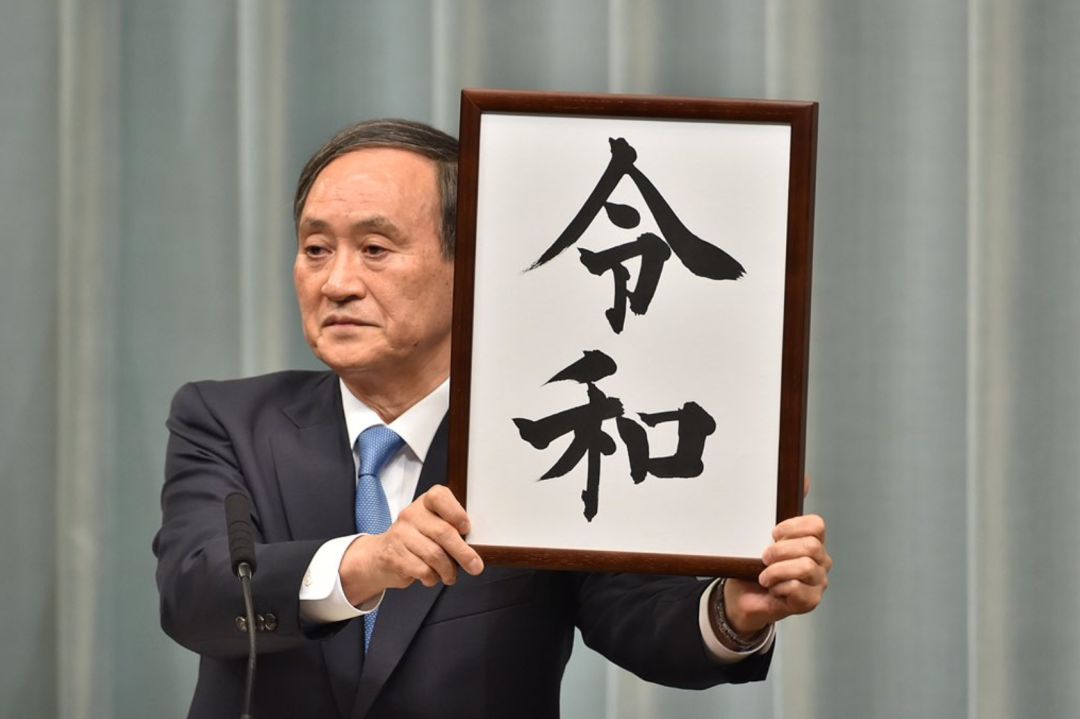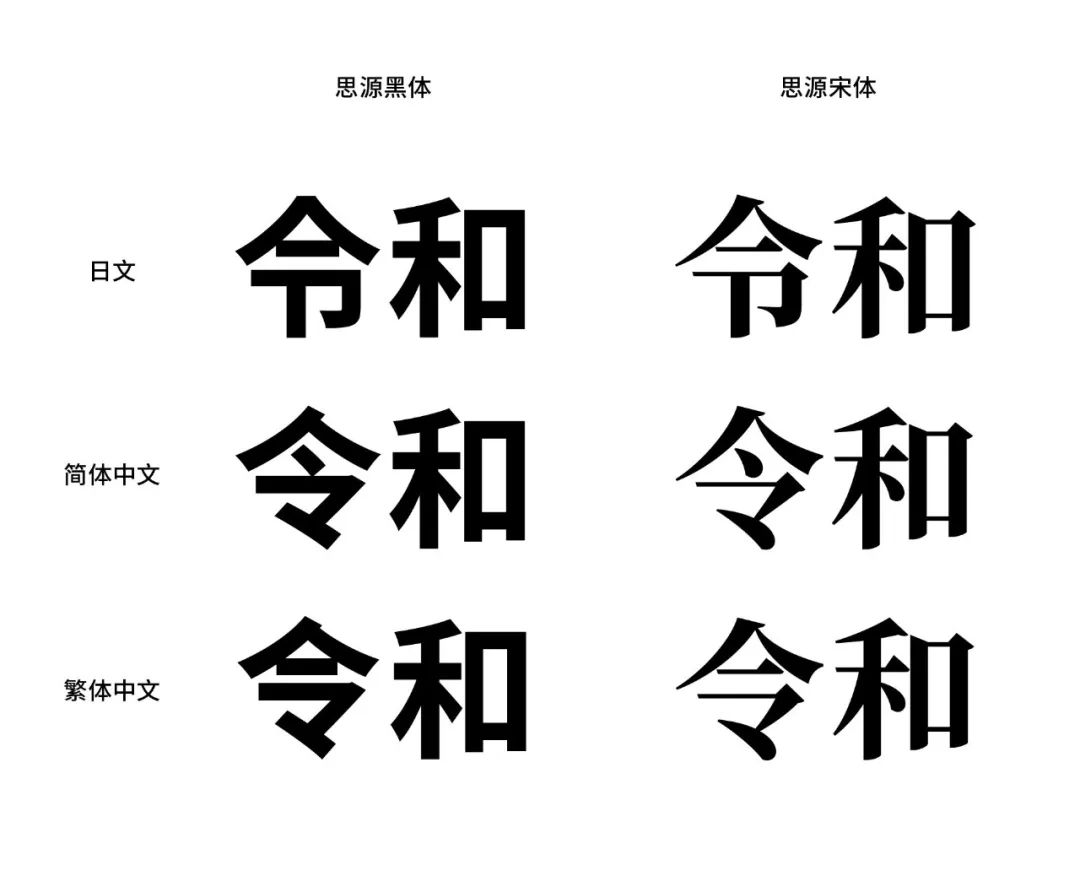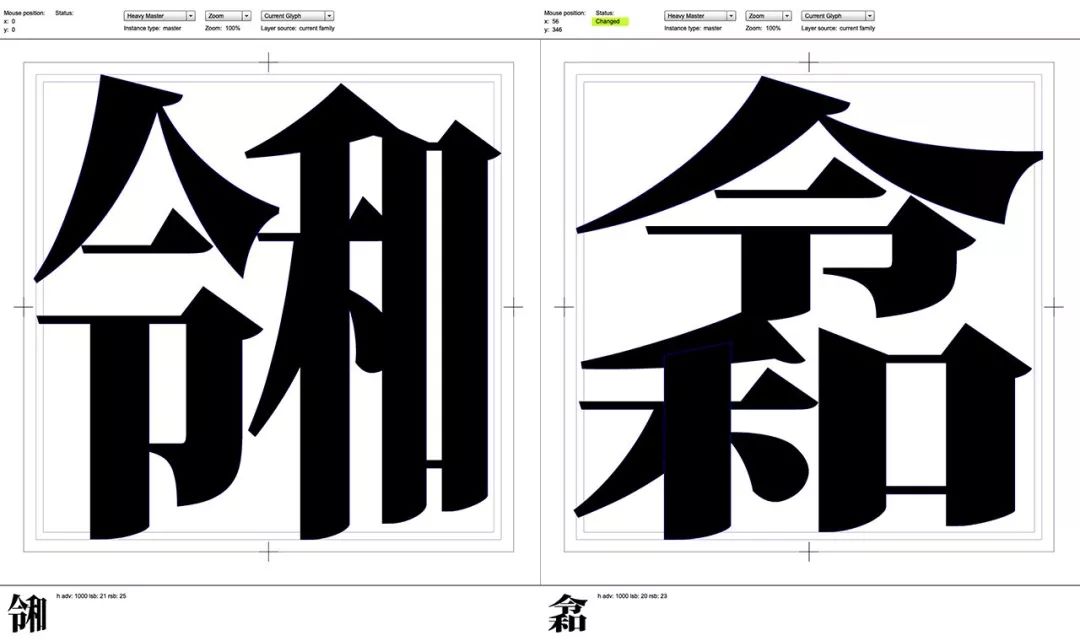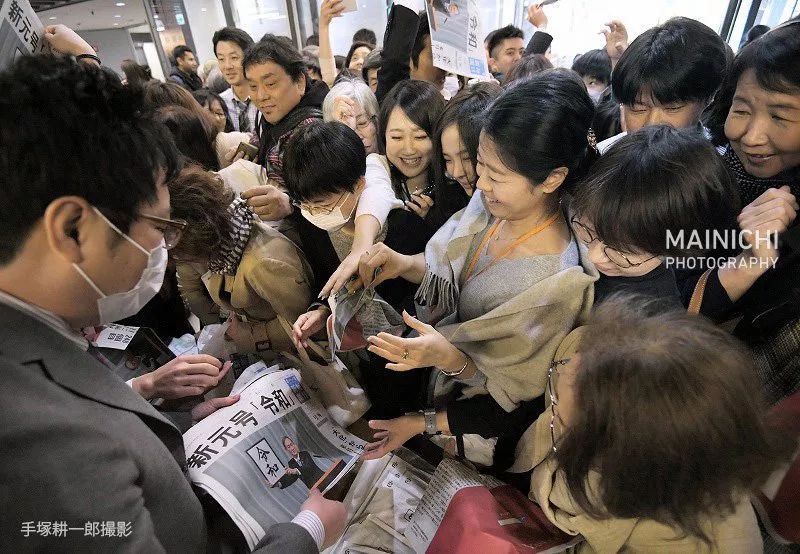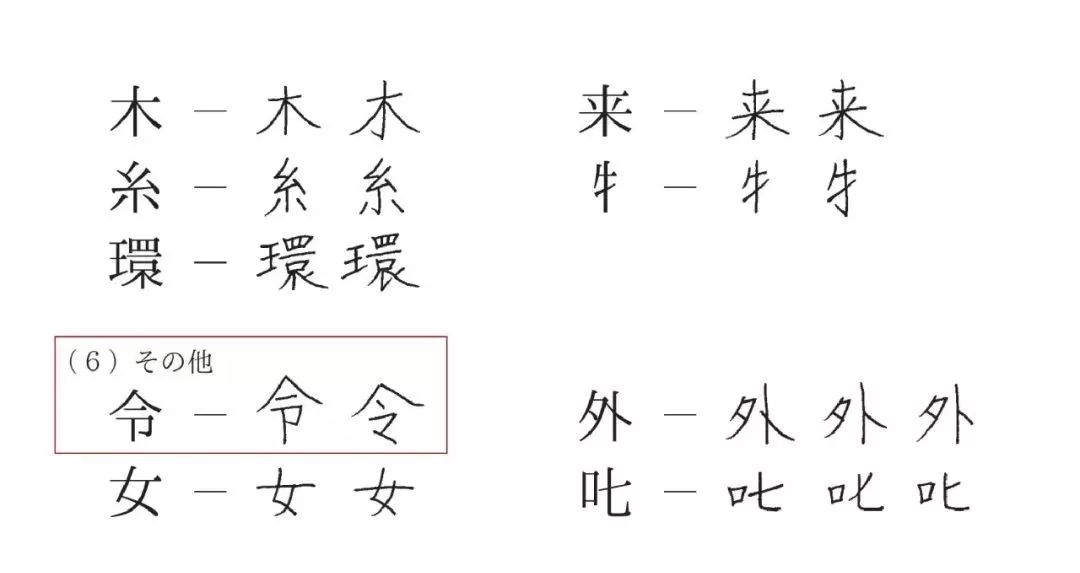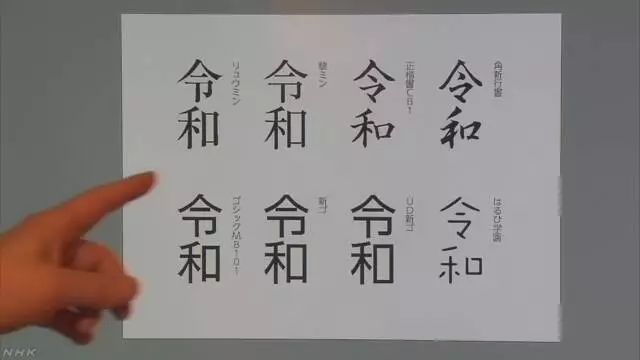
关于日本新年号「令和」,你可能不知道的五个事实
最近,日本政府严肃地在首相府邸召开新闻发布会,正式宣布下一轮年号名称为「令和」。在字体设计师眼中,改年号不仅是国家层面上的大事,对实际业务也有直接的影响。小编在 twitter 上关注了不少字体设计师,整理了一些关于「令和」的有趣事实,让我们和日本人民一起来凑个热闹吧:
❶
年号的「合字」
年号对于日本人来说是非常重要的汉字组合,所以字体厂商们往往会把它们做成 「合字」,将两个文字压缩在一个全角文字的空间内,既彰显了年号的威严,又会显得更整齐美观。比如之前的年号,是这样显示的:
㍾ ㍽ ㍼ ㍻
昨天年号刚发布之后,Adobe Font 就抓紧赶工制作年号合字,随即发文说明他们的小塚明朝体、小塚黑体(小塚ゴシック)和思源黑体(源ノ角ゴシック)日语及泛中日韩的版本,「令和」的合字已经更新完成。
Adobe Fonts 发布的小塚明朝体合字预览
由于日本保留了竖排阅读的习惯,所以在制作合字的时候必须同时制作横排和竖排的合字。制作的时候不仅仅是把两个字压扁然后放在一个框里,在一个全角字框里塞满两个字的同时要保证可读性和优美程度,字体设计师得使尽浑身解数才能做到完美。
❷
中日文的「令」不一样
大家都知道日文使用汉字,但实际上日汉字和中文汉字时常有一些细微的区别。比如“天”字,在日汉字里是上面的横比下面长,小编刚学日语的时候按照中文来写,就被老师打了个大大的 ❌。在「令和」中,「令」字也是个不老实的家伙,它在日文、简体中文和繁体中文的汉字造型都不大相同。如上图,以开源字体思源字体家族为例,「令」字的造型各不相同,正在学习日语和繁体字的朋友们可要多加注意了。
❸
日文的「令」也有好几种写法
不仅日文和中文的「令」有细微的差别,其实日文的「令」也有好几种写法。如上图所示,主要有两个地方的不同:人字头下面的点是横还是点;下半部分的整体造型是「卩」还是「マ」。不同的字体厂商也会根据字体的种类和风格选择采用哪种方案,似乎并没有一个定论。
日本有一个叫做《常用汉字表》的汉字规范,里面归纳了一般的新闻报刊以及日常生活中所用到的2136个字以及书写规范。其中在手写体的「令」中就有两种写法:
《常用汉字表》
进一步地,在《关于常用汉字表的字体字形的指示》(『常用漢字表の字体字形に関する指針』)文档中,对「令」的不同写法又有了更多的归纳:
《关于常用汉字表的字体字形的指示》
针对这个问题,日本文化厅的回复是「没有正确的答案」。在指示文档中,文化厅的观点是,汉字造型无法完全统一是书写习惯造成的,本来就不是一个问题,因此也不需要确定一个说法。
❹
「令和十八年」= R18 ?
🔞
日本改年号有几个规则,其中一个便是首字母不能与之前的年号重复,因为简写的时候常写成「首字母+年数」的形式。比如今年是平成三十年,也会记作H30。本次的「令和」罗马音是「reiwa」,首字母是「R」,也是小编最喜欢的一个西文字母。不过,这个小「R」也引发了推特网友的热烈讨论:因为R在电影分级制度中也会被使用,那么到了令和十八年就会简写成「R18」,即「十八禁」之意,2036年代表了🔞?关于改年号的讨论在推特上持续火热,日本网友真可谓是脑洞大开。
❺
改年号还要发「号外」
看过抗日神剧的朋友们大概都知道「号外」是什么,当有突发重要新闻时,报社便立即赶制版面,一个多小时后于当地街头派发,以求将消息尽快提供给读者。现代社会连报纸都几乎无人问津,但日本仍然保留了发「号外」的习惯。年号发表当天下午1点左右,各大报社纷纷开始在各大车站发放「改元」号外,抢夺的人群络绎不绝。
有趣的是,报社除了发布实体的号外,还在官网上发布pdf版本的「电子」号外。上一次改年号还是在三十年前,数字排版尚处萌芽时期,pdf版本的号外是不可想象的。让我们来看看各大报社的「号外」分别长什么样:
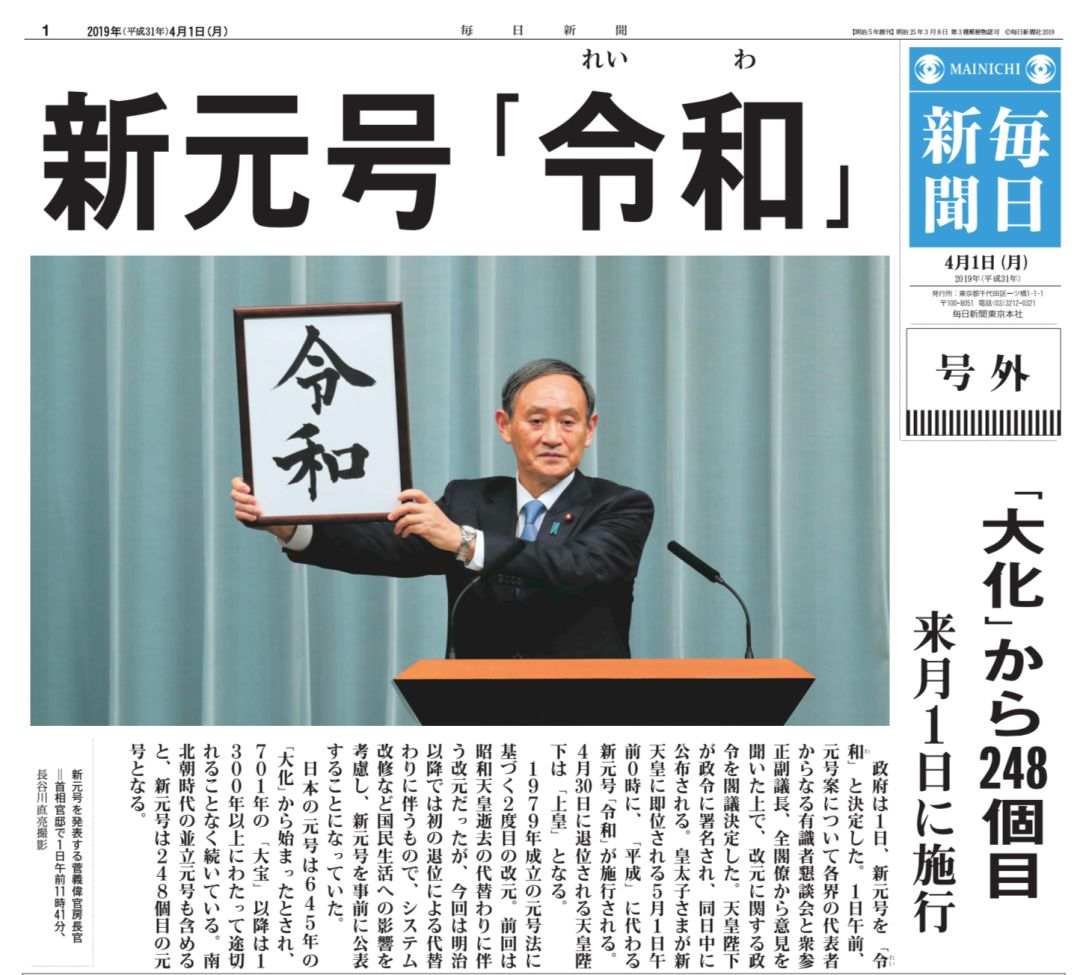
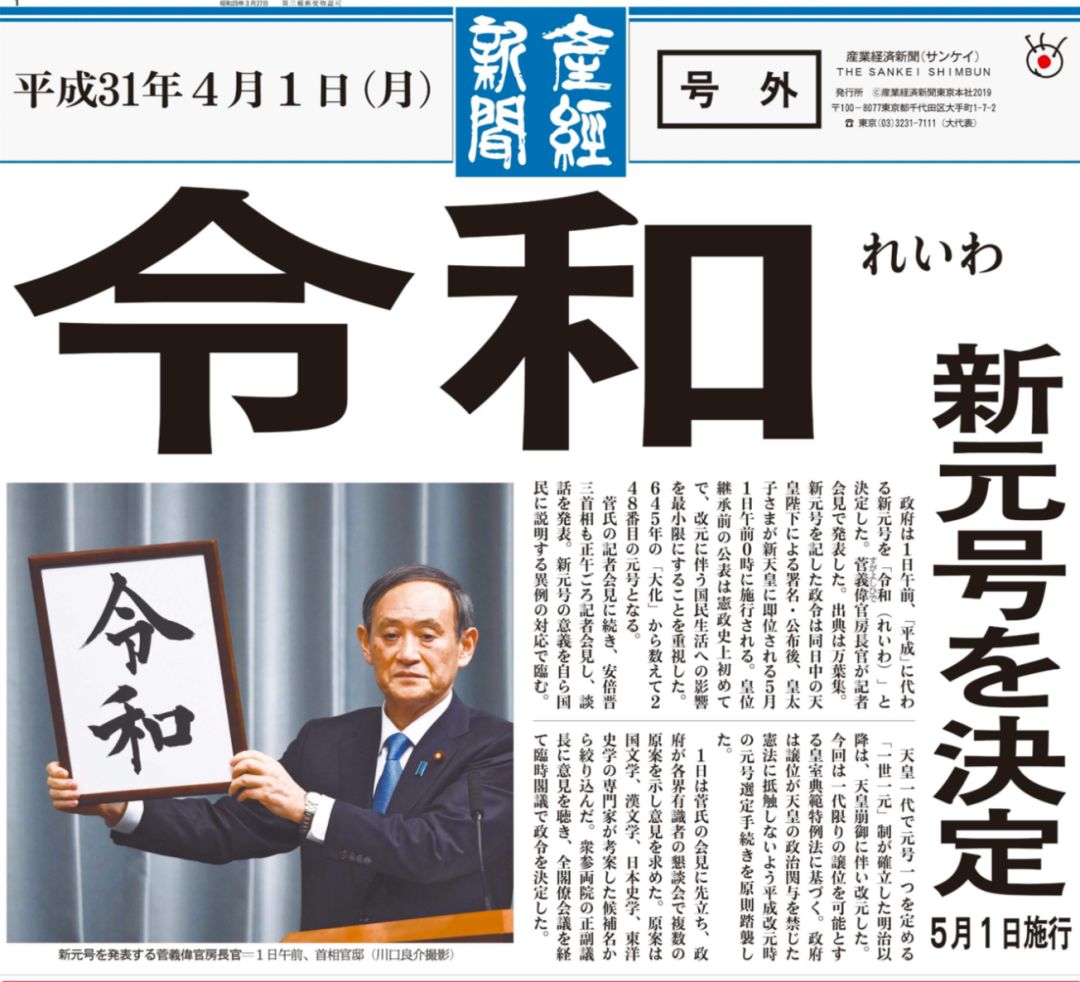
热闹凑够了,最后来看看日本画家野村一晟书写的从平成到令和的「颠倒字」,博大家一笑: